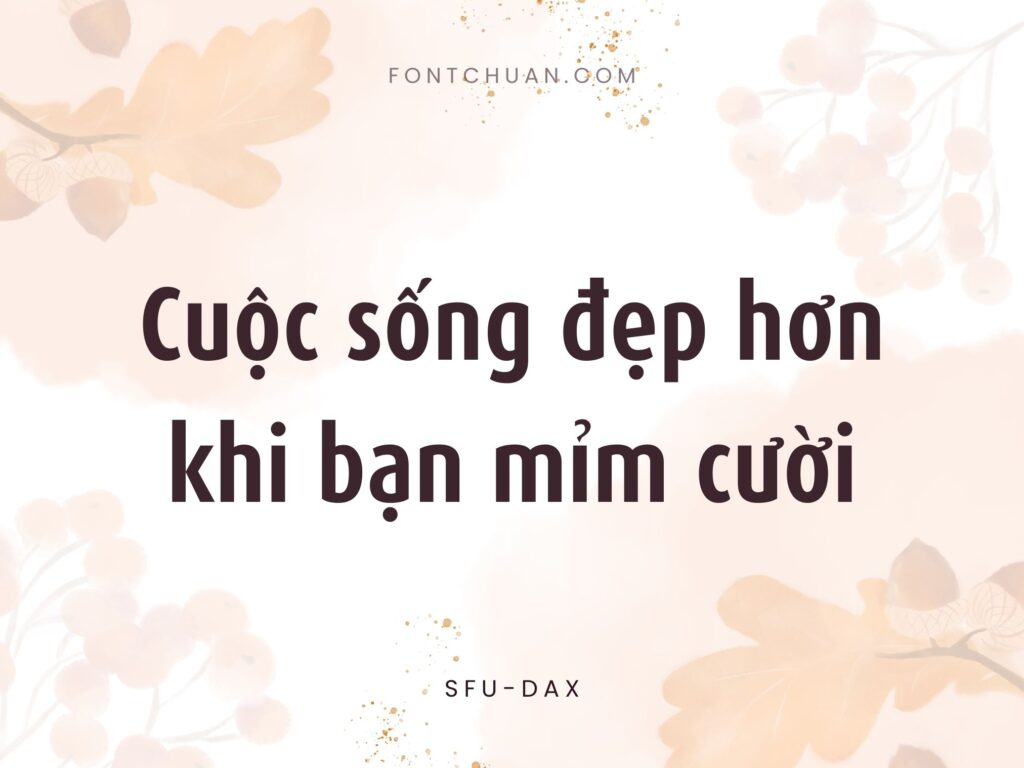
Font Dax là một kiểu chữ sans-serif hiện đại, được thiết kế bởi Hans Reichel và phát hành lần đầu vào năm 1995. Với các đường nét gọn gàng và tinh tế, Dax mang lại cảm giác thanh lịch và chuyên nghiệp, phù hợp cho nhiều mục đích thiết kế khác nhau như in ấn, thương hiệu, bao bì sản phẩm và thiết kế kỹ thuật số. Phiên bản SFU-Dax đã được Việt hóa, hỗ trợ đầy đủ tiếng Việt, giúp người dùng dễ dàng ứng dụng trong các dự án đa ngôn ngữ
Về đặc điểm thiết kế, Dax có cấu trúc chữ cái rõ ràng, với các đường cong mềm mại và khoảng cách giữa các ký tự được tối ưu hóa để đảm bảo tính dễ đọc. Kiểu chữ này rất phù hợp để sử dụng trong các thiết kế như tiêu đề, văn bản nội dung, bảng hiệu và các ấn phẩm quảng cáo
Font Dax được ứng dụng rộng rãi trong các sự kiện như lễ hội, ngày Nhà giáo, Giáng sinh, Halloween, Tết, Valentine, Trung thu. Nó phù hợp với nhiều ngành nghề như quảng cáo, giáo dục, công nghệ, bất động sản, ẩm thực, thiệp cưới